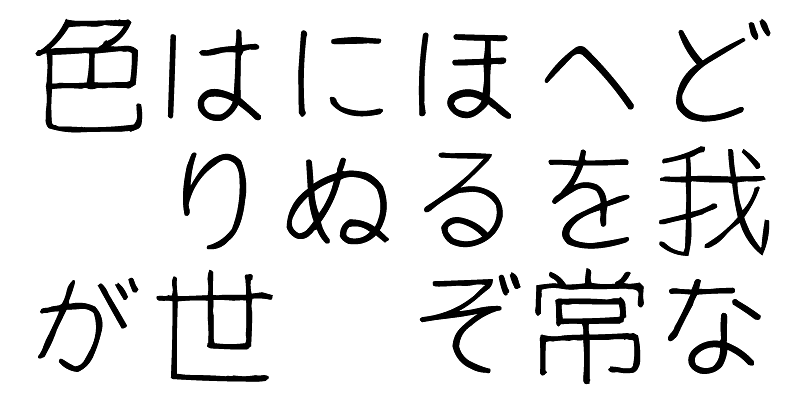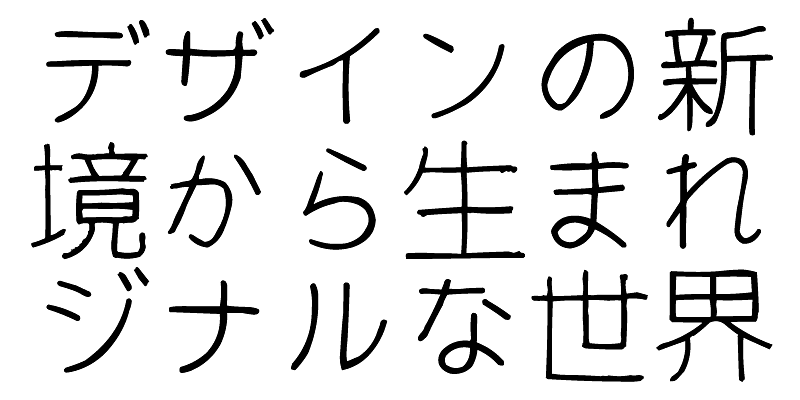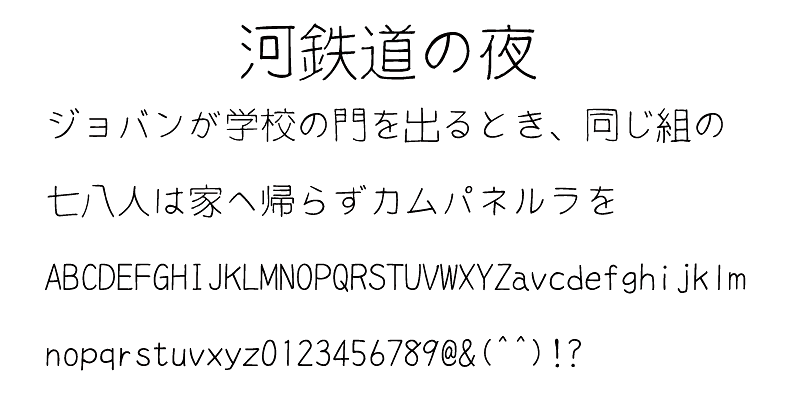
Cette série de polices contient des polices japonaises originales écrites à la main basées sur la calligraphie au stylo publiées en 2002. Avec leur look chaleureux, ces polices attireront l’œil du lecteur sur les points clés d’un design.